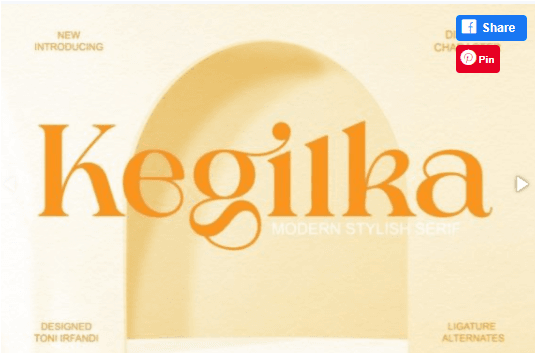
Кегилка Шрифт
Kegilka Font
Kegilka — очень харизматичный и стильный шрифт. Пересечение его кривых настолько плавное и красивое, что делает ваш проект аккуратным и особенным.